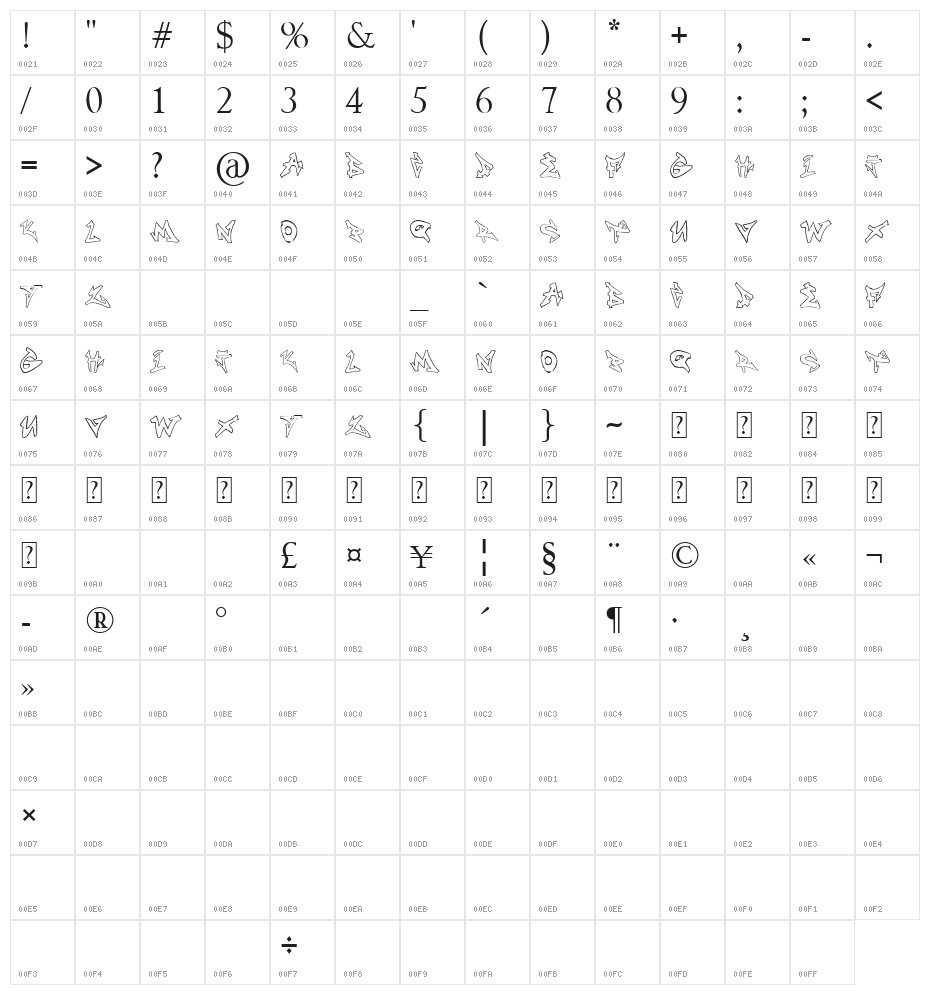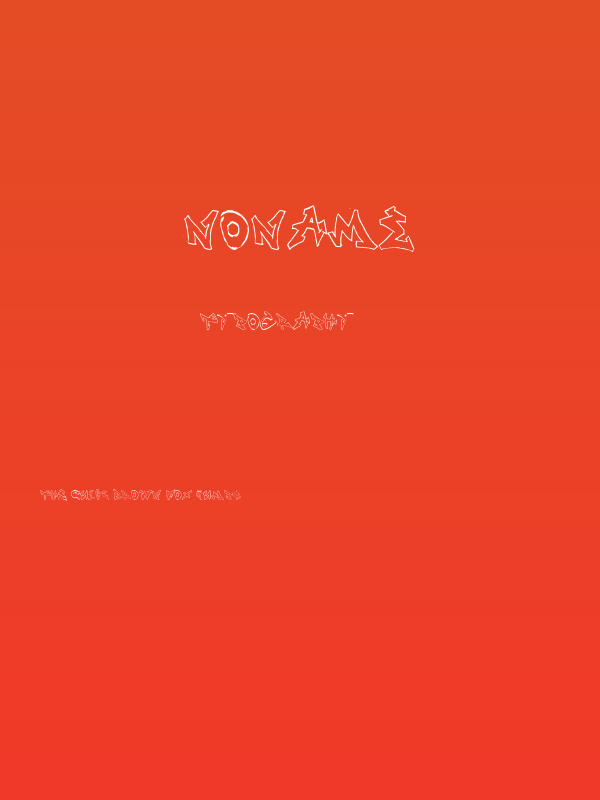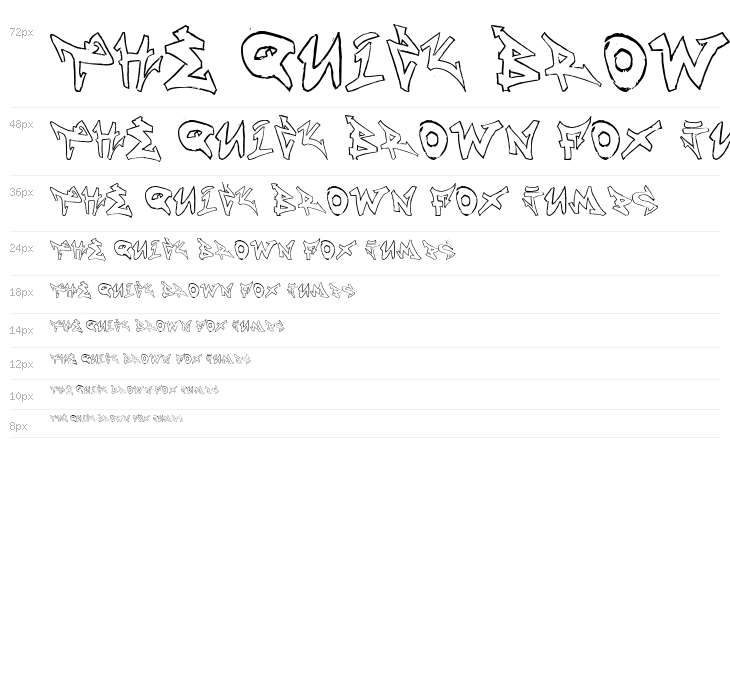
NONAME Font
✎ Graffiti
NONAME MAIUSCOLE
NONAME MINUSCOLO
NONAME ALTRI CARATTERI
| Categorie | Graffiti |
| Stile generale | Modern, Urban |
| Caso d'uso | Logos, Posters, Headlines |
| Progetti proposti | Perfect for street art posters, music album covers, urban-themed branding, and edgy graphic designs. |